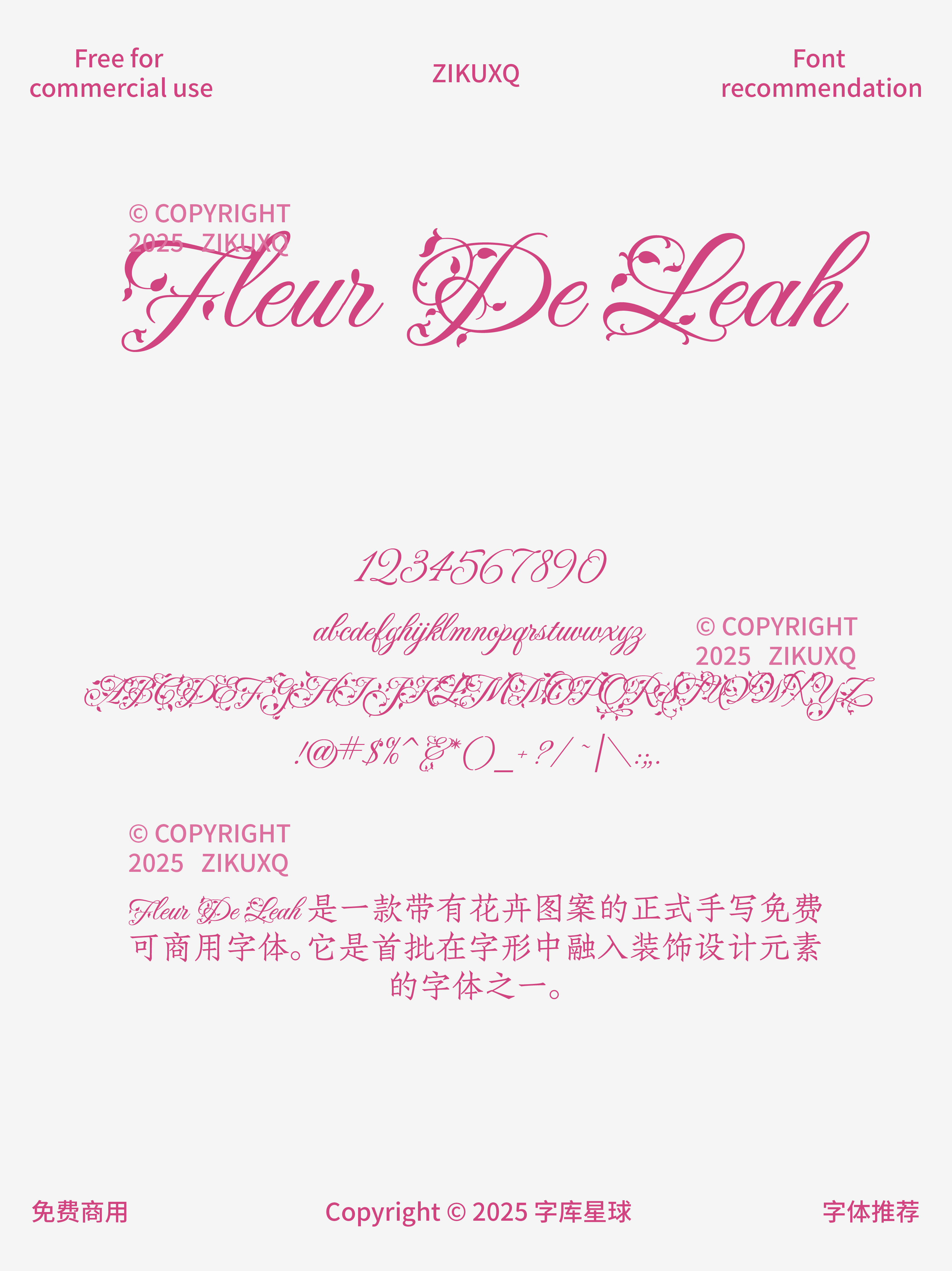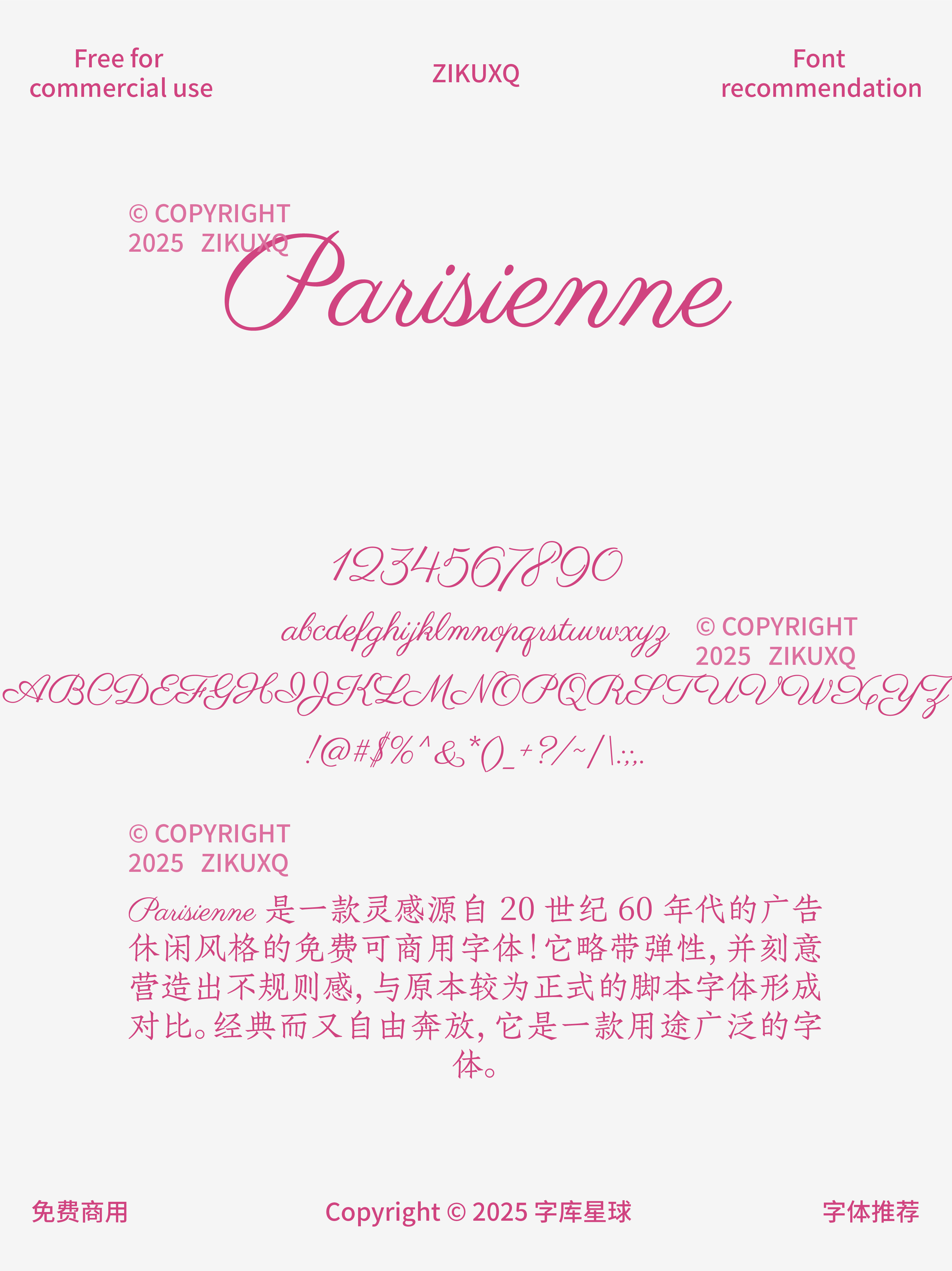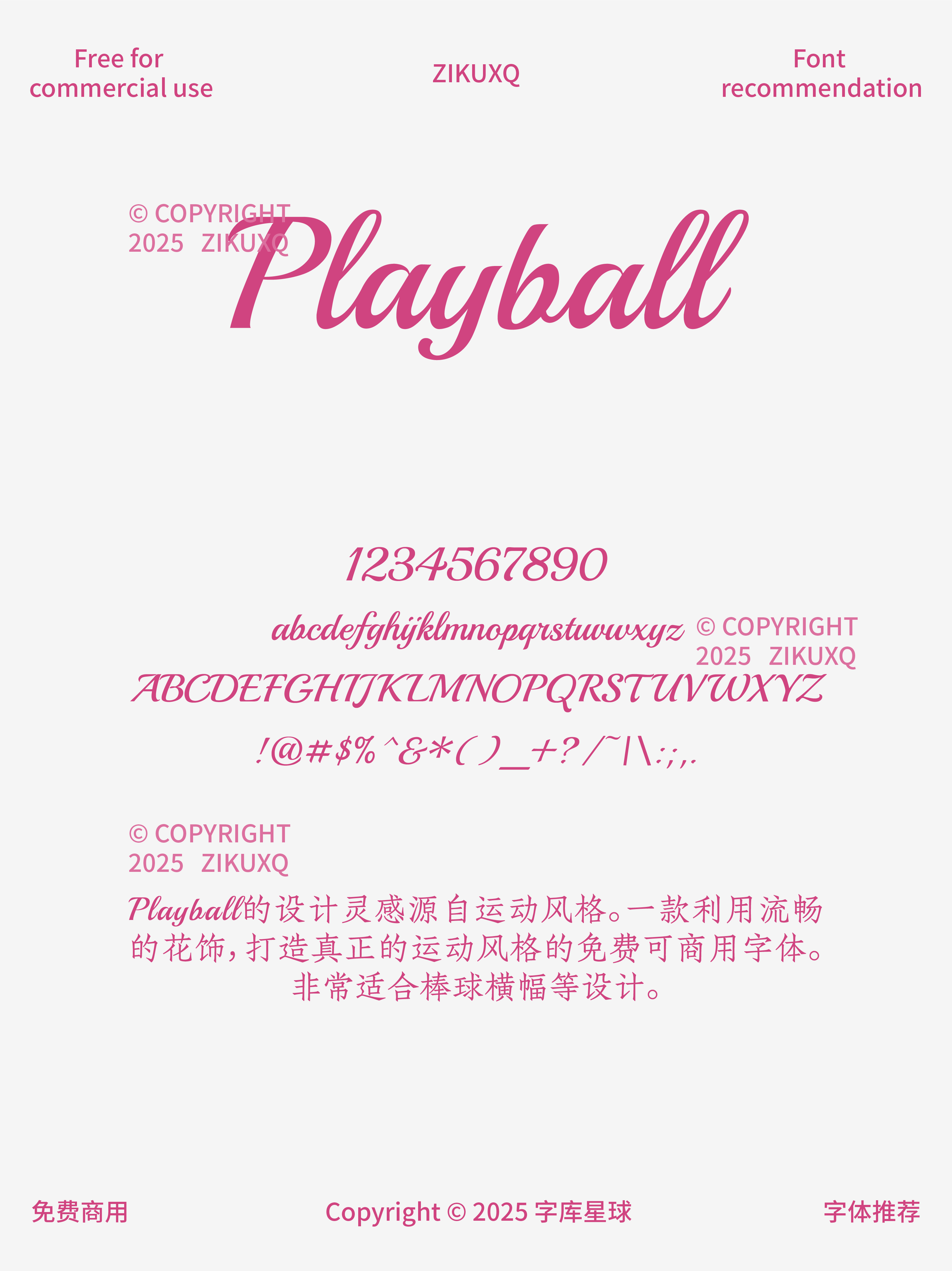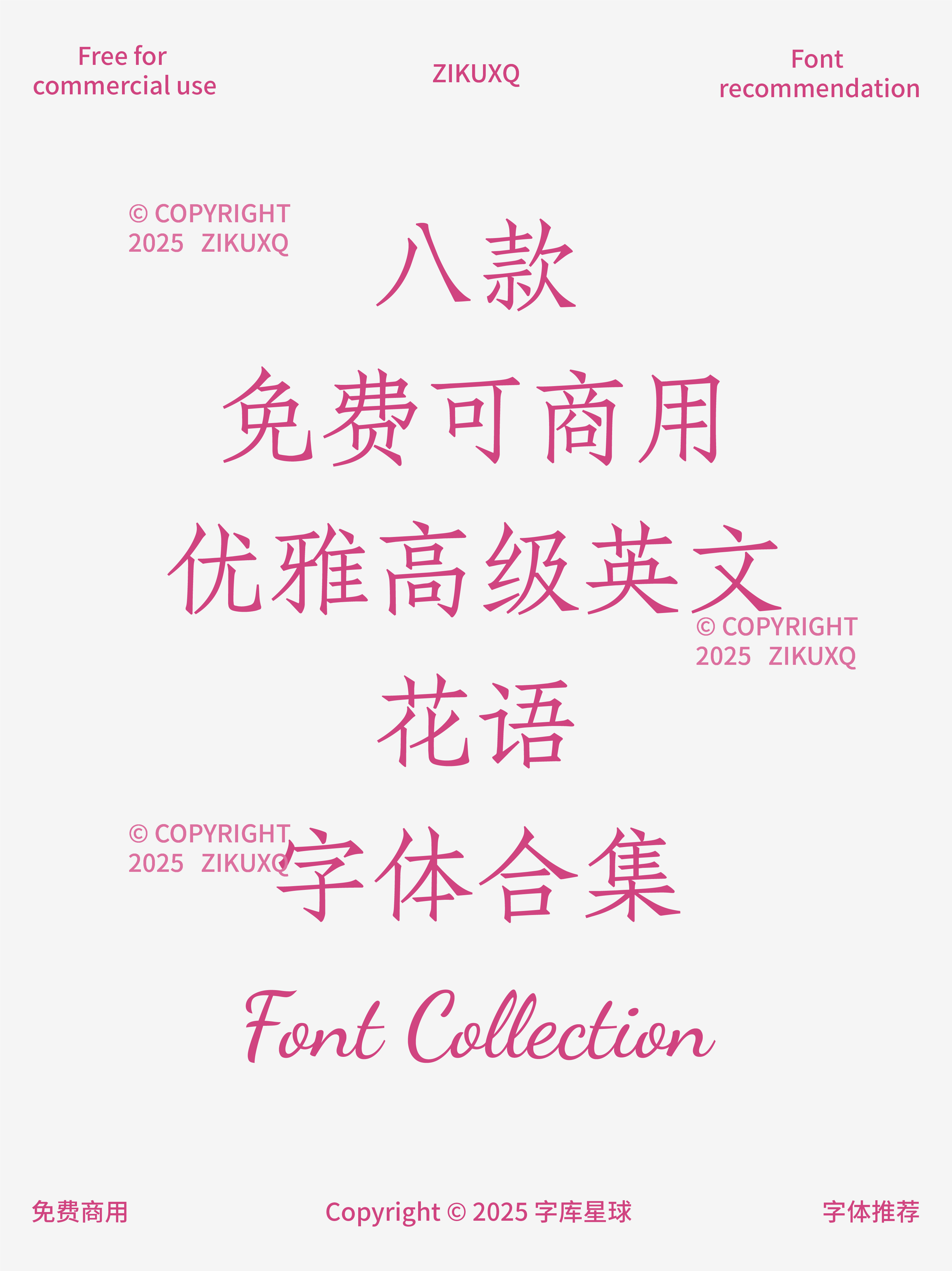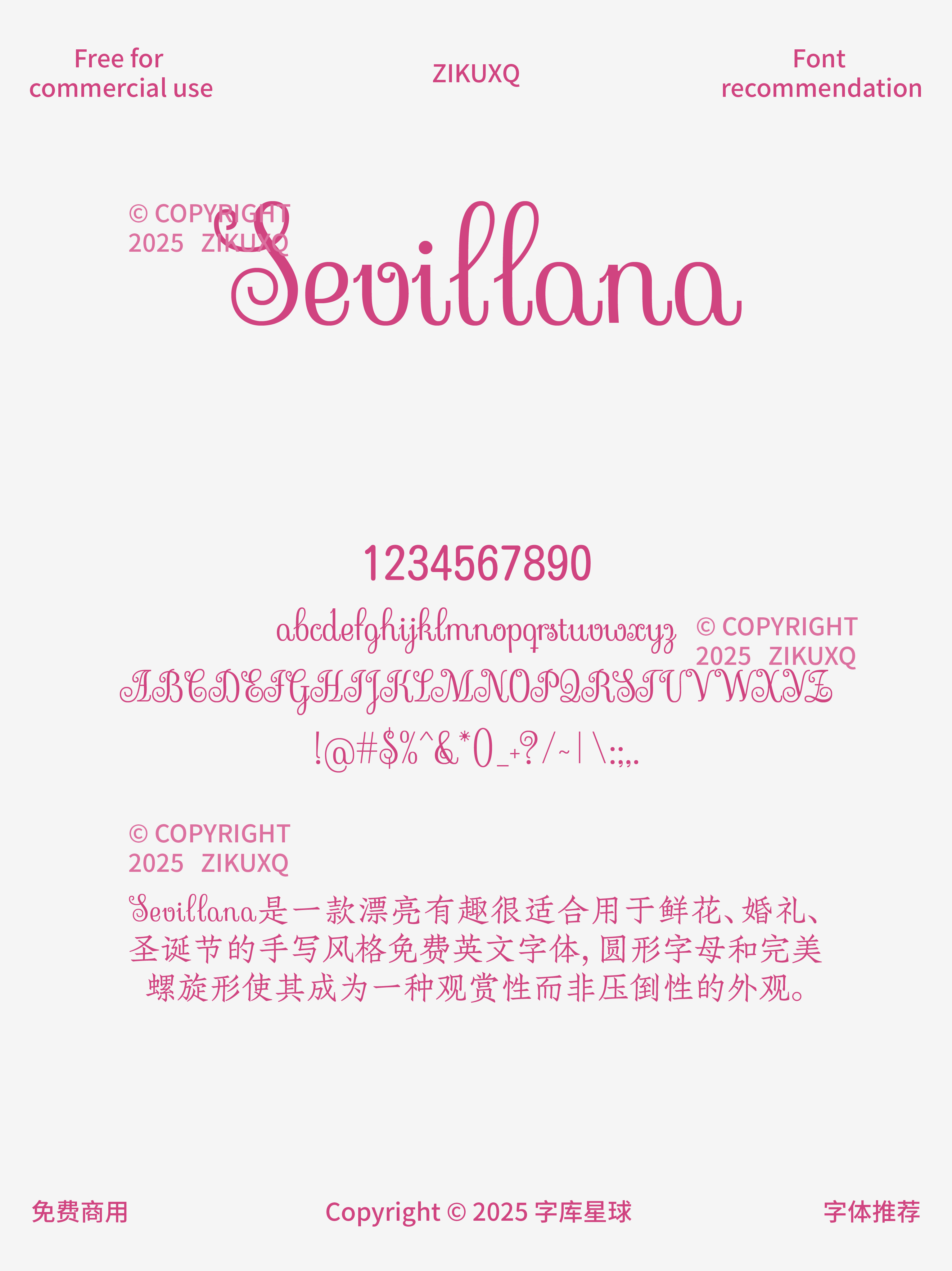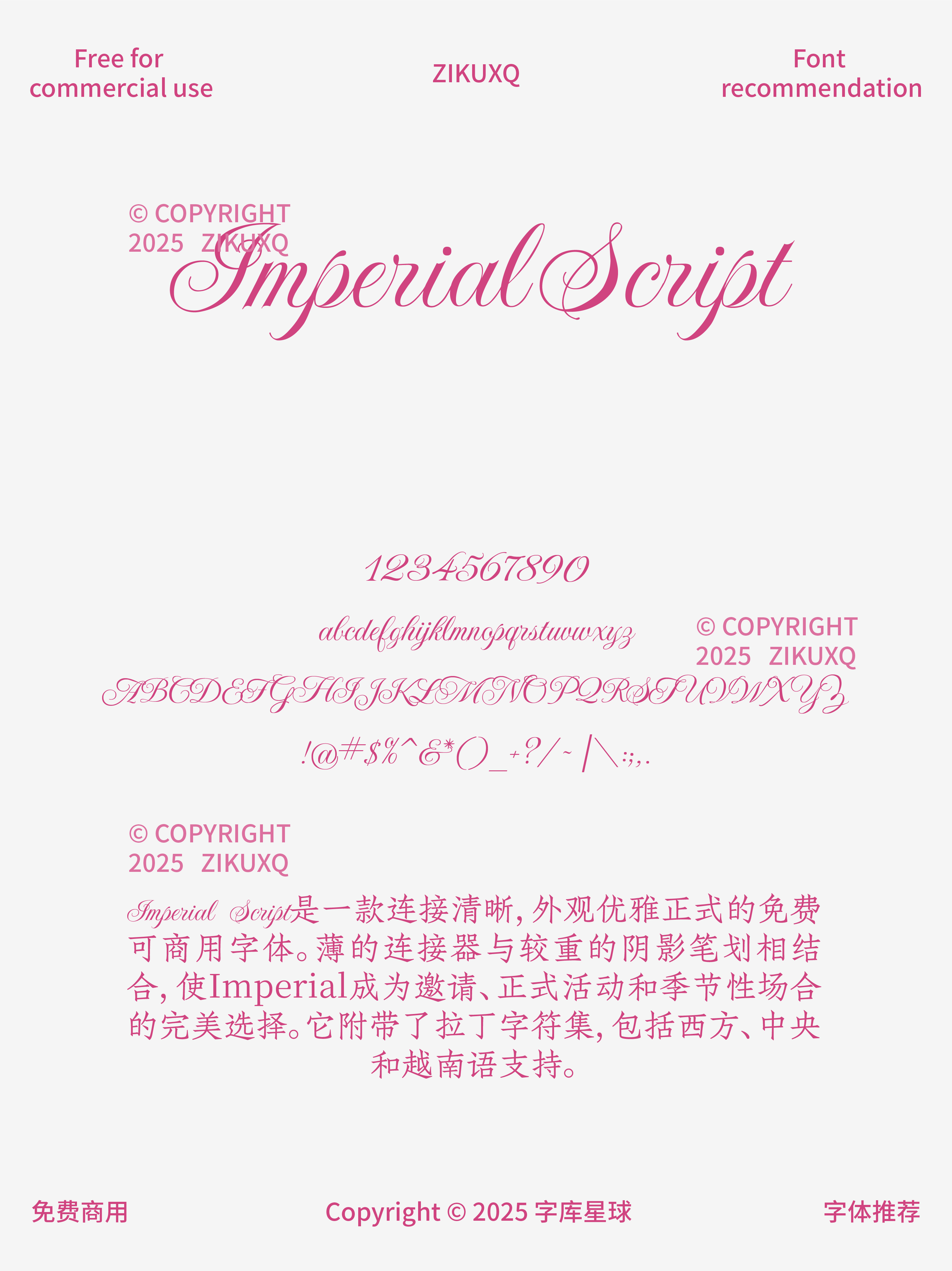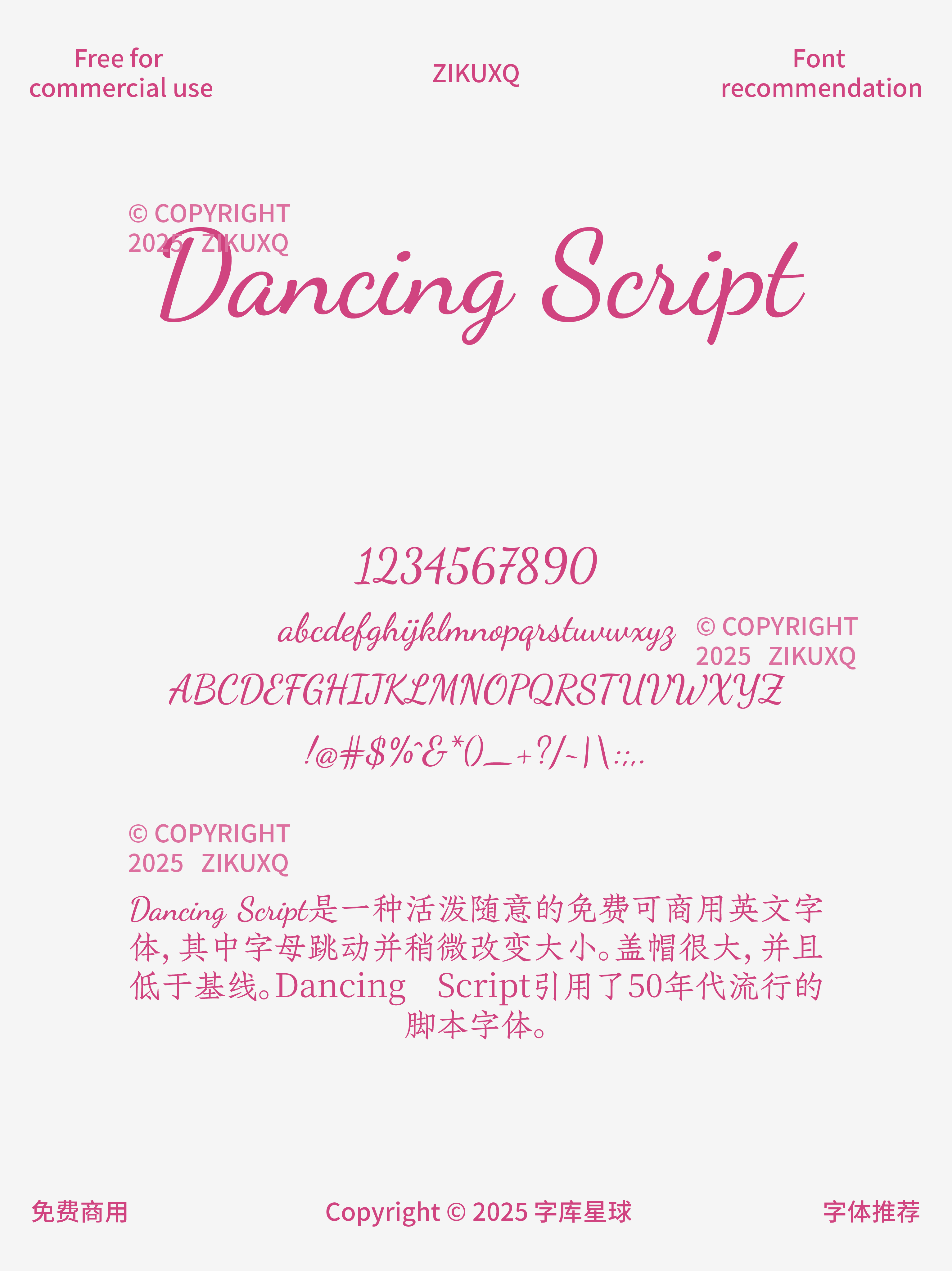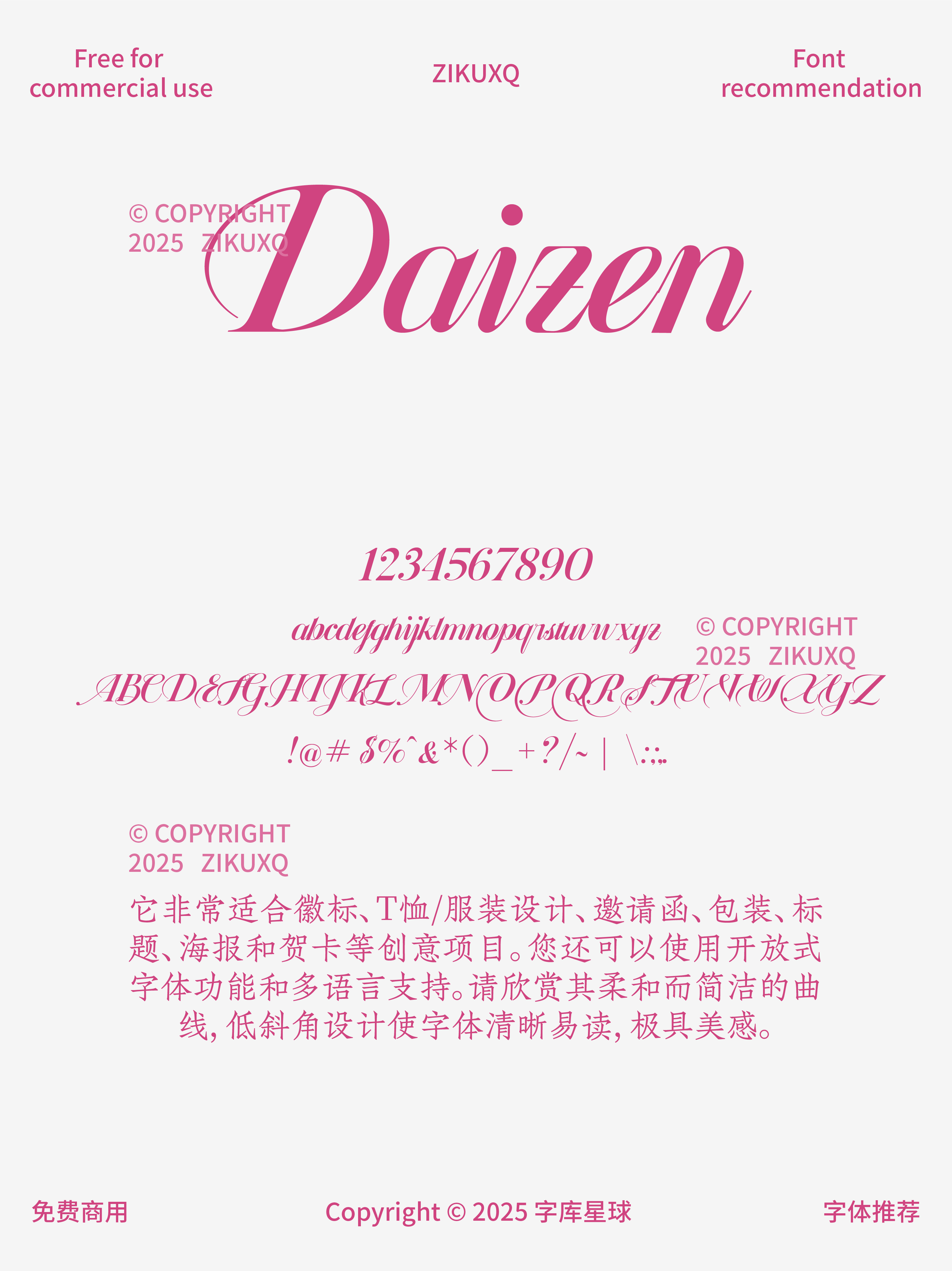
八款免费可商用优雅高级英文花语字体
今天给大家分享八款超美的免费可商用英文花语字体,用它们能给作品瞬间增添优雅高级感,赶紧码住!
经典衬线花体,优雅浪漫的气息扑面而来,用于婚礼请柬、花艺海报,简直绝绝子,能营造出超梦幻的氛围。衬线与花体结合的现代标题字体,个性又吸睛,在创意广告、潮流店铺招牌上,能大放异彩。独特的手写花体,充满艺术感,在艺术展览海报、小众品牌包装上,展现与众不同的魅力。